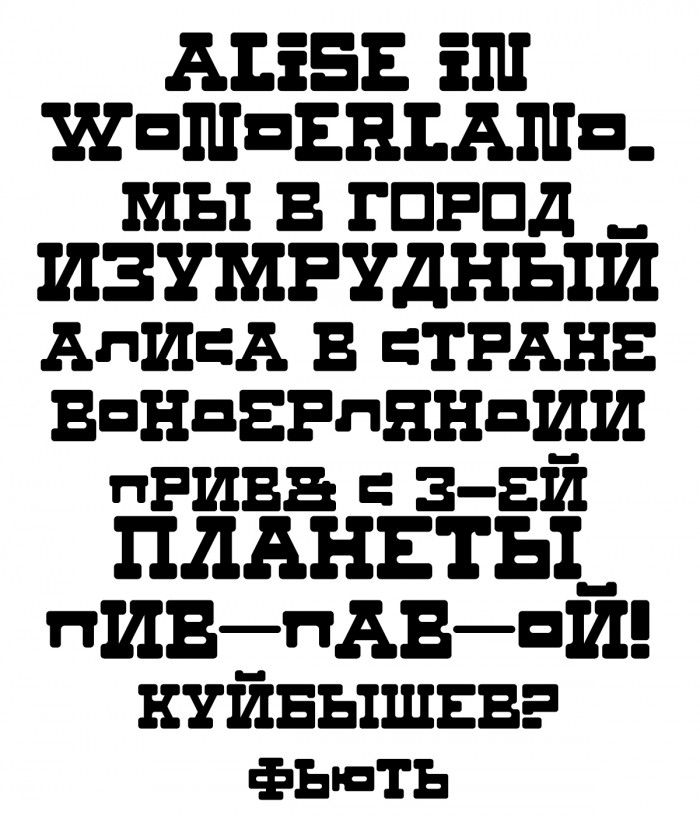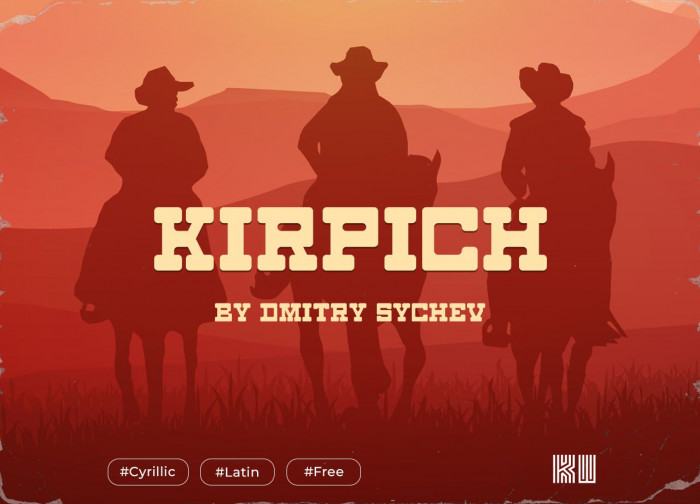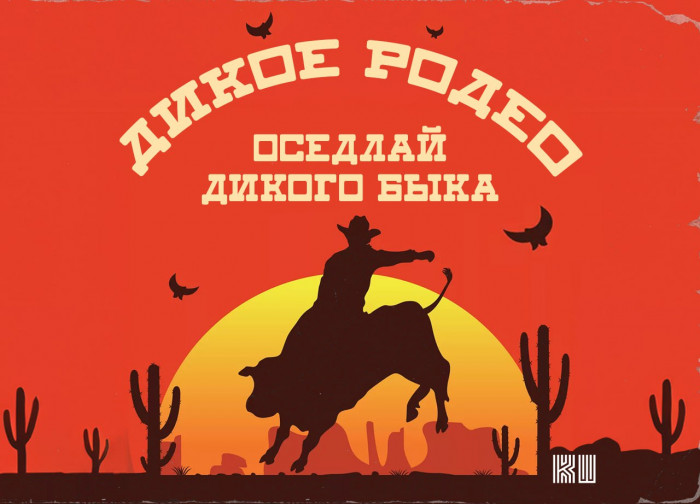
cool how you manage the design with the ciryllics
Крууууууууууууууто. А зачем маленькие буквы?
Кстати, имя: «Alise» — не правильно; должно быть: «Alice».
@ TCM: See his previous posted samples ;-)
@TH3_C0N-MAN: Это была намеренная ошибка, я захотел показать букву S.
Интересный вопрос. Изначально я мало разбирался в шрифте и в Фонтструкторе, когда делал этот шрифт, поэтому даже сделал бруски-засечки, чтобы не мучиться с острым окончанием А. Мне не понравилось, какими получаются круглые буквы, было слишком много белого внутри, из за чего они ощущались как дырки (хотя тогда я ещё не знал про теорию письма Ноордзея, соотношении белого и чёрного и делал всё интуитивно). Решил попробовать сделать "по-другому", примерил это к другим округлым буквам, и понял, что прыгающая строка выглядит забавно и раньше я такого не видел. Потом я узнал, что этот приём широко использовался в Америке в 60-ых. В итоге получился отличный шрифт для детских книжек про приключения, в котором обратный (вестерновский или итальянский) контраст почти не заметен.
Ага да я теперь вижу шаблон.
Wowow Good Old Time Font